フォントの日 2025年4月10日にリリースされたフォント
ニコイチ
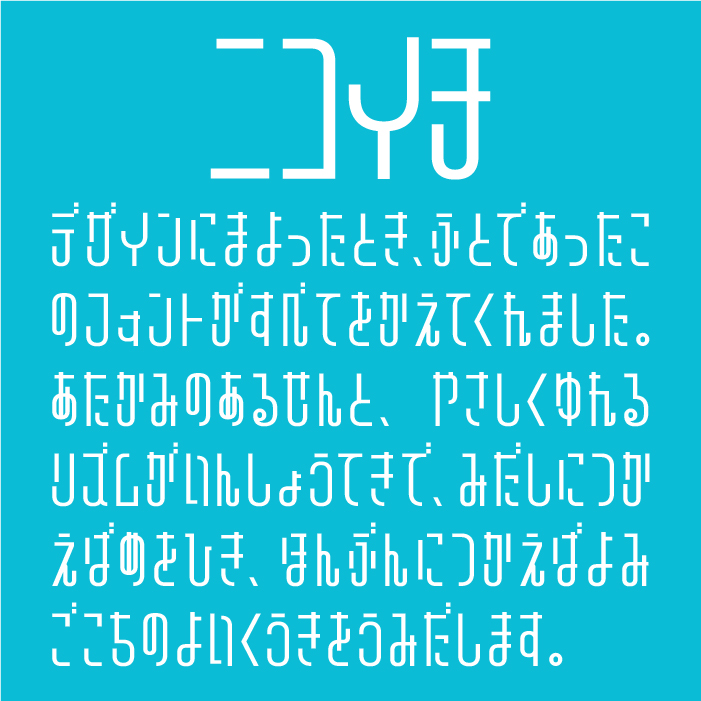
ニコイチフォントは、直線的で整理されたミニマルな構成ながらも、どこかかわいらしい丸みがあるデザインフォントです。字形・縦横線のコントラスト・傾きの3つの軸を自由へ可変できるバリアブルフォントです。
LVDC とろぴの
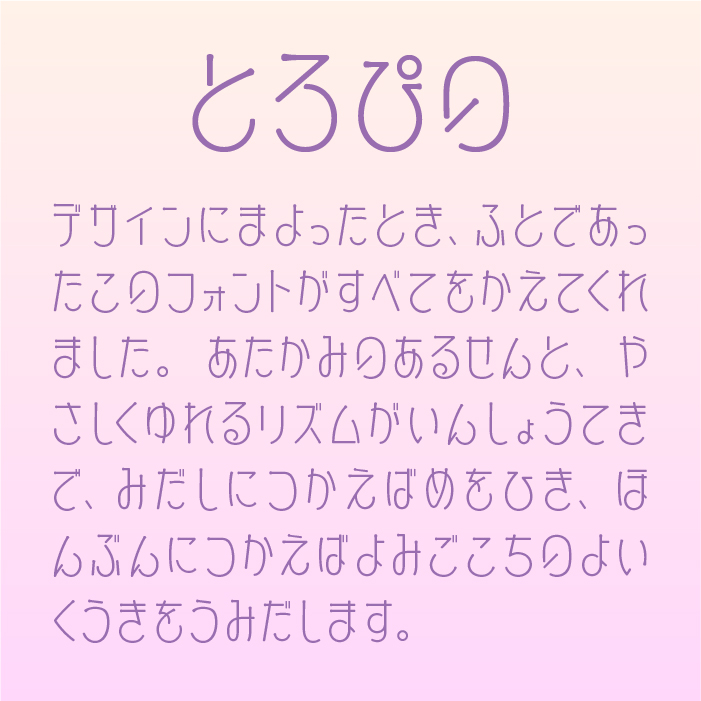
LVDC とろぴのフォントは、ゆるくとろけるような曲線が特徴で、ひらがな特有の丸さが強調された癒し系フォントです。
縁架ドット明朝24
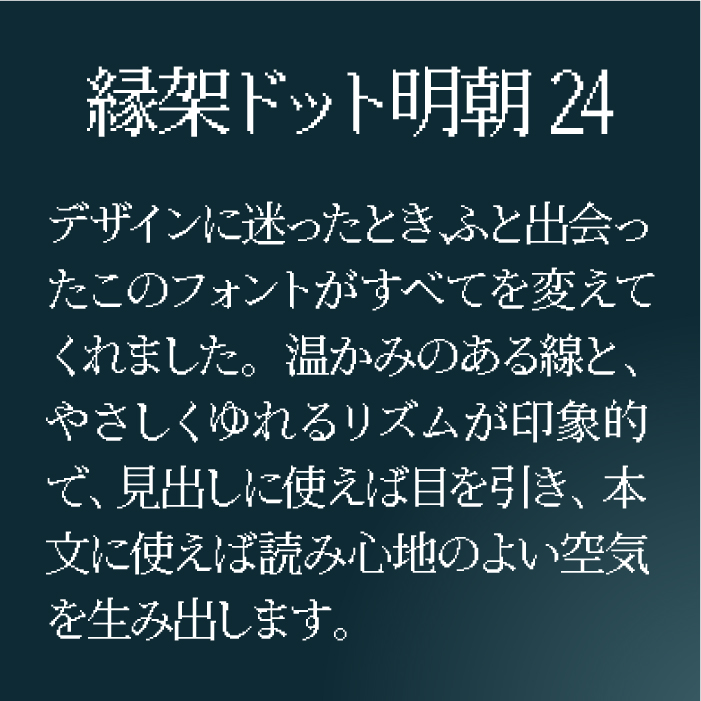
縁架ドットゴシック24フォントは、NotoSerifをベースにレトロゲームのようなドット表現されたユニークな明朝体フォントです
縁架ドットゴシック24
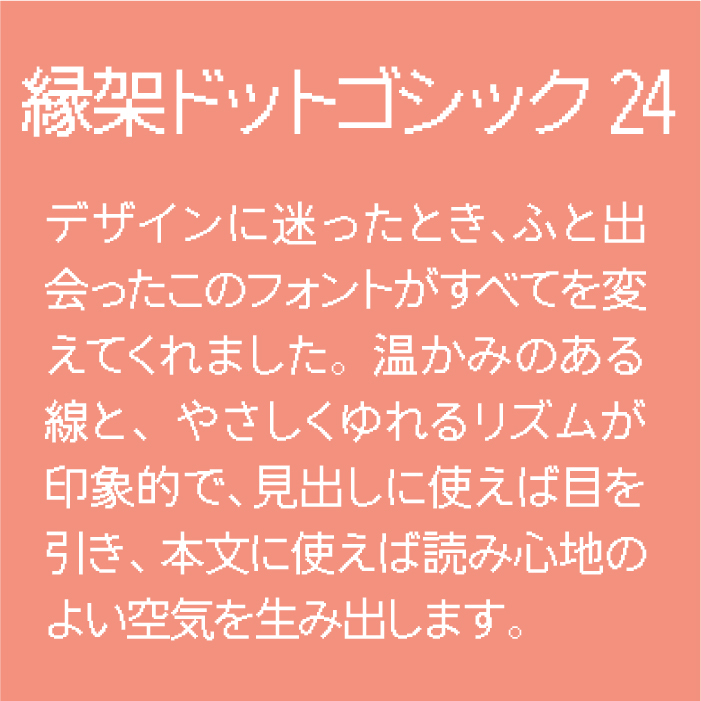
縁架ドットゴシック24フォントは、NotoSansをベースにレトロゲームのようなドット表現されたユニークなゴシック体フォントです
山びこやま
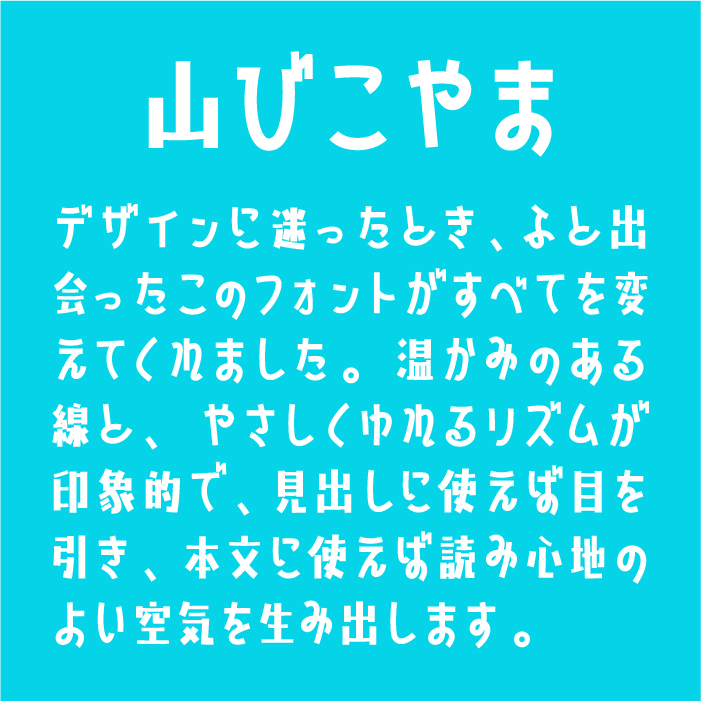
「山びこやま」フォントは、どっしりとした縦長文字にユニークな揺らぎを加えた、親しみやすくも可愛らしいフォントです。
ICHIGAYA明朝
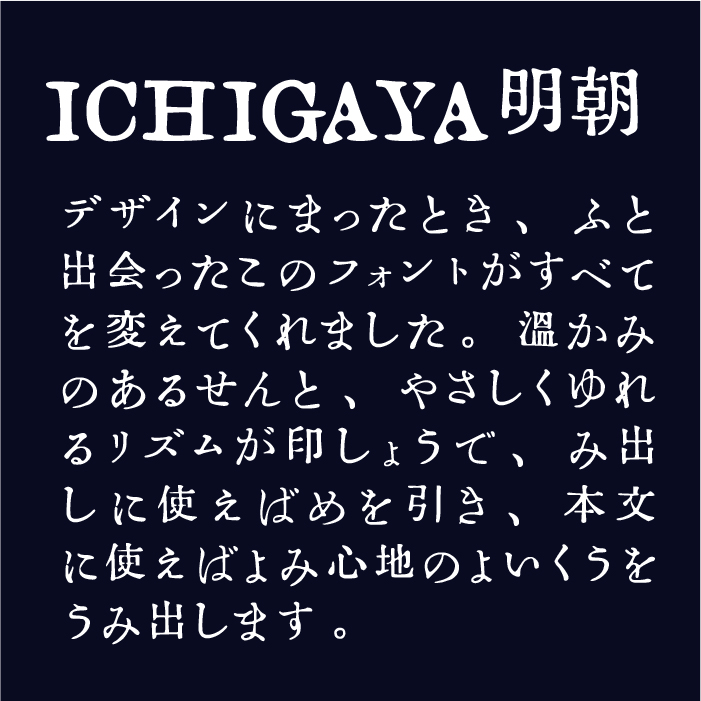
ICHIGAYA明朝体フォントは、秀英舎活版製造所の活字をベースに制作された明朝体フォントです。
はいぱーキャンディ
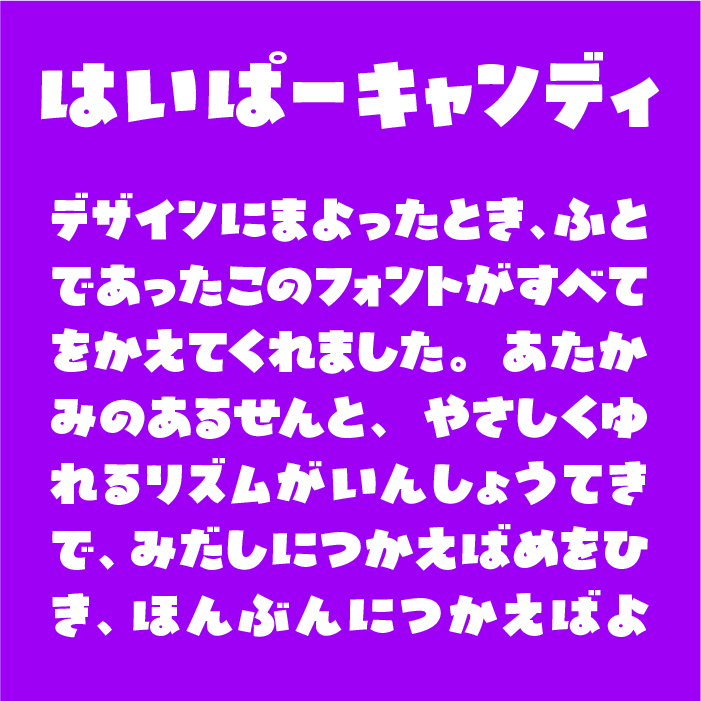
「はいぱーキャンディ」フォントは、太めでぽってりとした文字が弾むような印象を与える、元気でポップなフォントです。
higemoji pop font
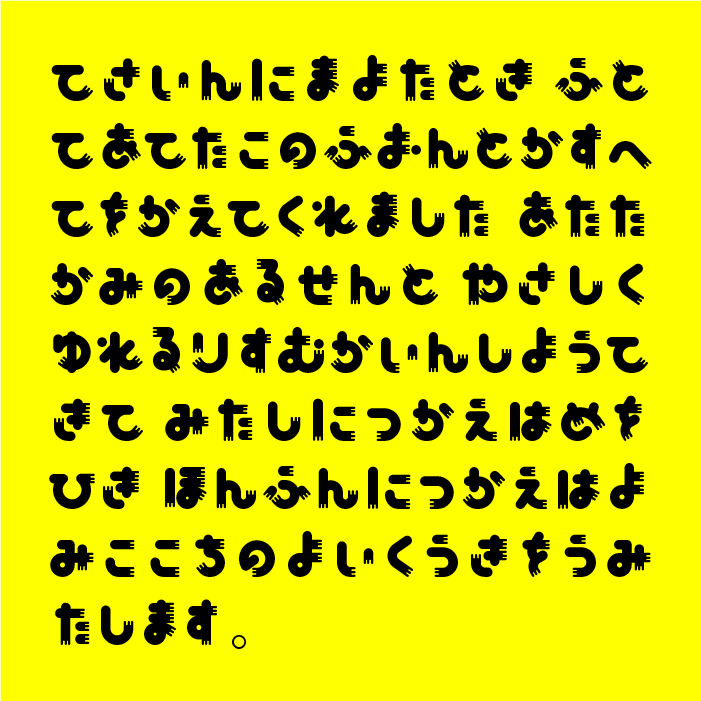
higemoji pop fontフォントは、丸みがある丸ゴシックにひげの装飾が施されているデザインフォントです。
LVDC OtsukaDream2
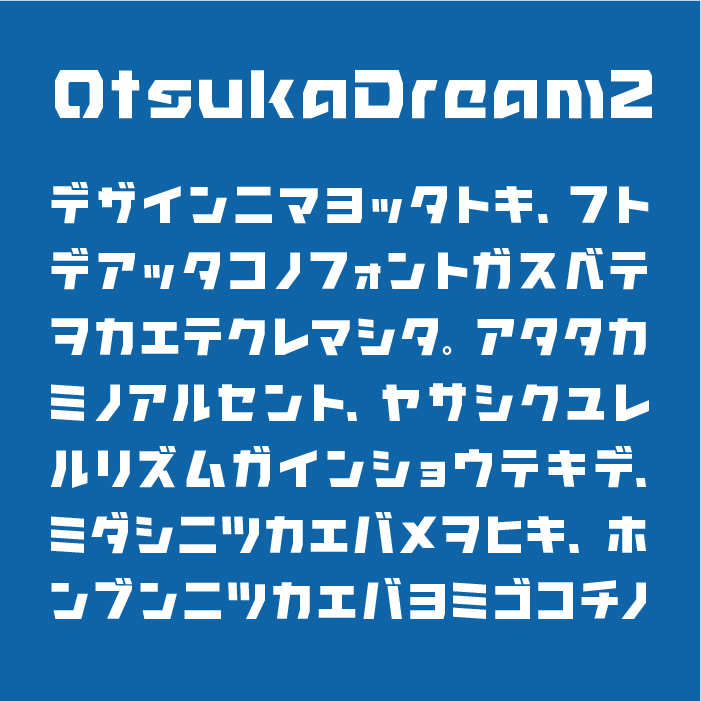
OtsukaDream2フォントは、カクカクとした直線と幾何学的なバランスが特徴の未来系デザインフォントです。
Seikoyuki筆文字フォント
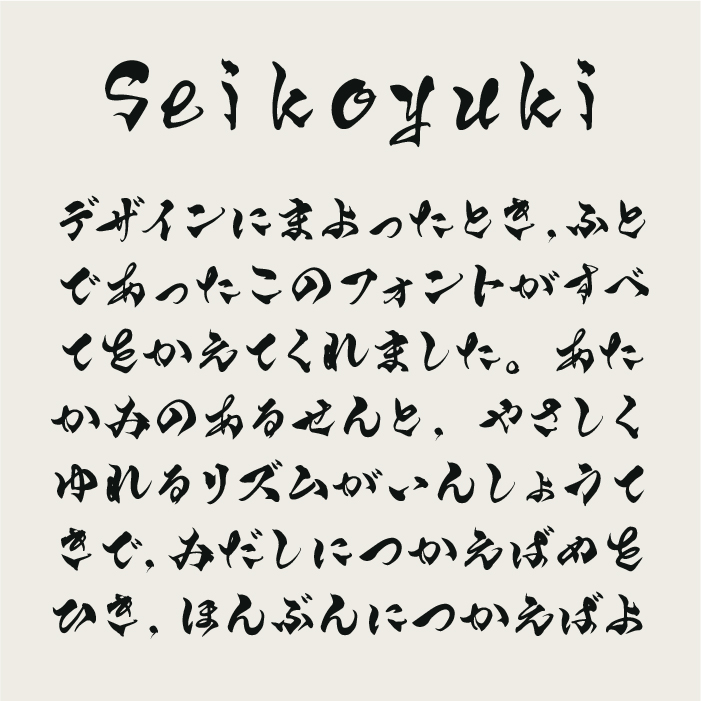
「Seikoyuki」フォントは、和風でありながらも柔らかく、力強さと繊細さが絶妙に共存しているエモーショナルな筆文字系フォントです。
雨墨ゴシック
雨墨ゴシックフォントは、デラゴシックをベースして、輪郭をギザギザなにじみの加工を施しているゴシック体フォントです。
なにくそ
なにくそフォントは、書道家・二階堂勇悦が制作した毛筆フォントです。
おまつりフォント
おまつりフォントは、丸みを帯びた太めの字形と、ほんのり跳ねるようなリズム感が特徴の、陽気でにぎやかなデザインフォントです。
ざわフォント
ざわフォントは、ポップでかわいいフォルムで、自然な手書き文字フォントです。
冥酸書華
冥酸書華フォントは、刺々しく攻撃的な印象が特徴のクールなデザインフォントです。
KFひま字ドット
ひま字ドットは、可愛らしい幼さを感じられるレトロなドットフォントです。
Melonano(メロナーノ)
Melonano(メロナーノ)フォントは、コミカルで可愛らしい極太なピクセルフォントです。